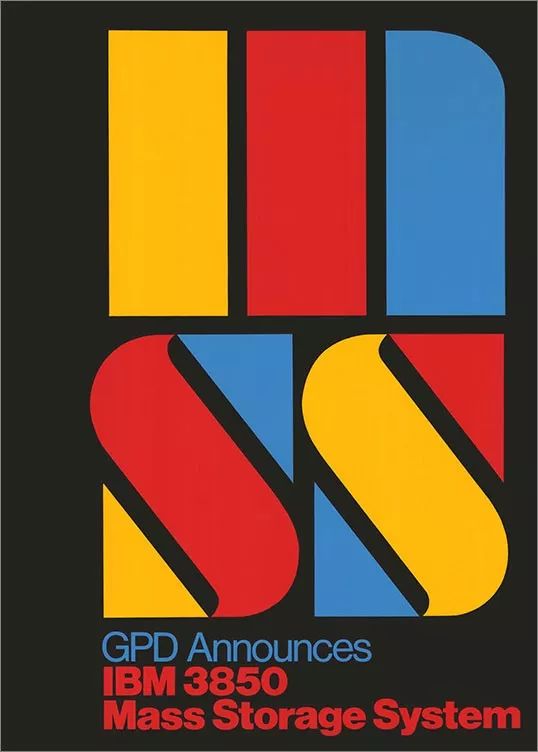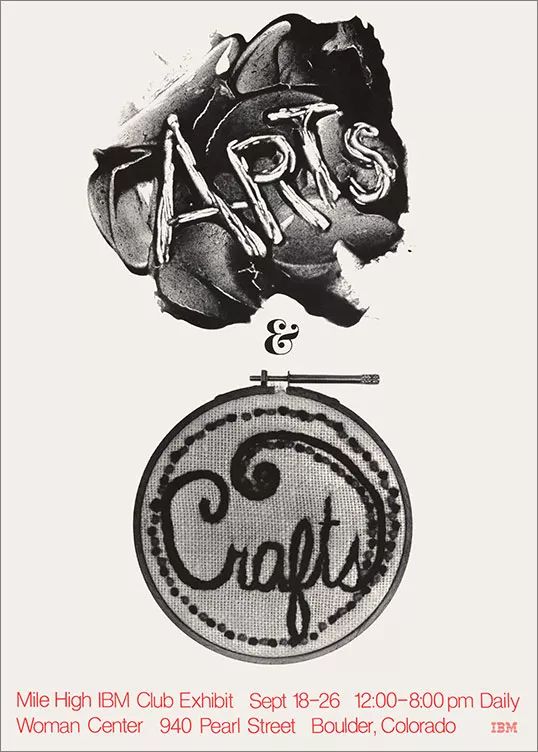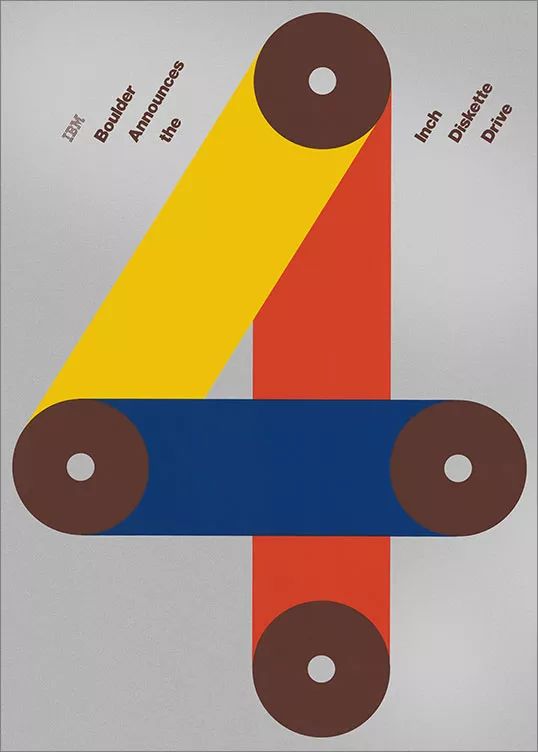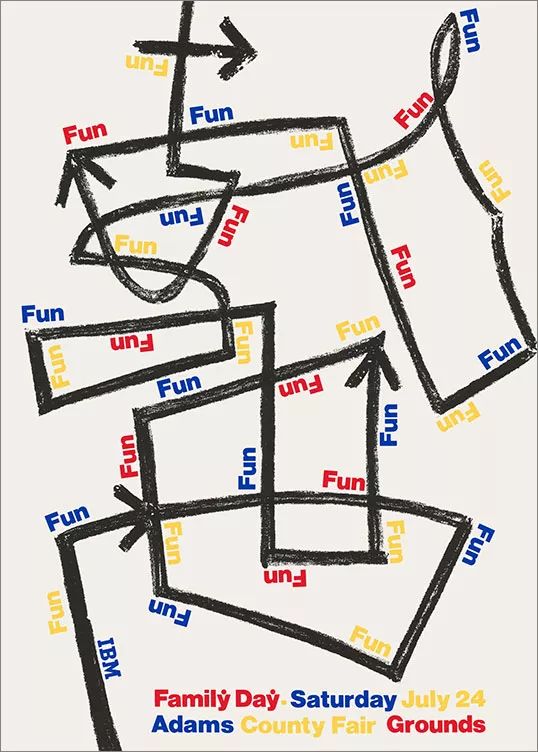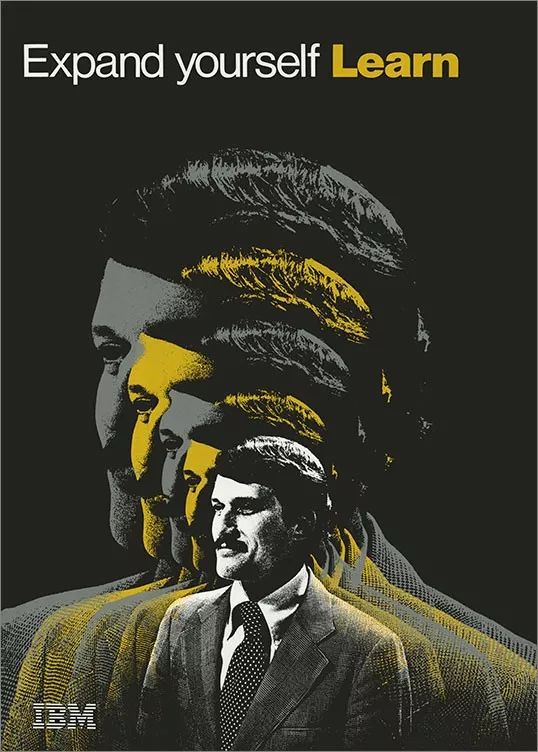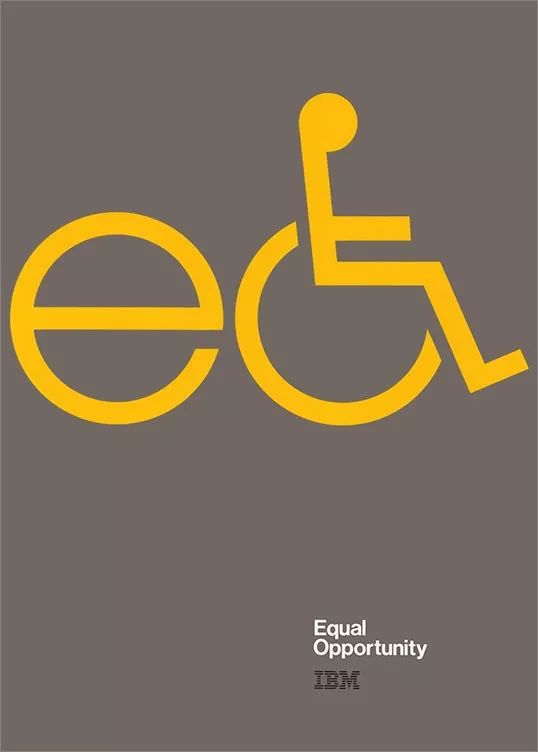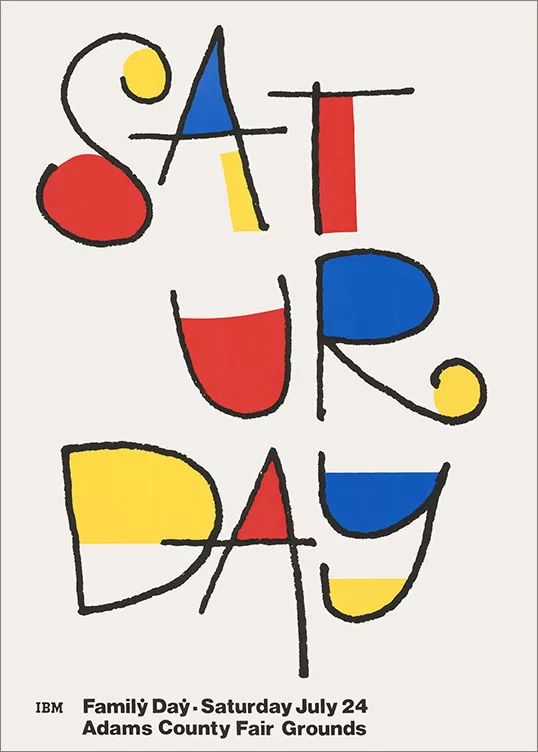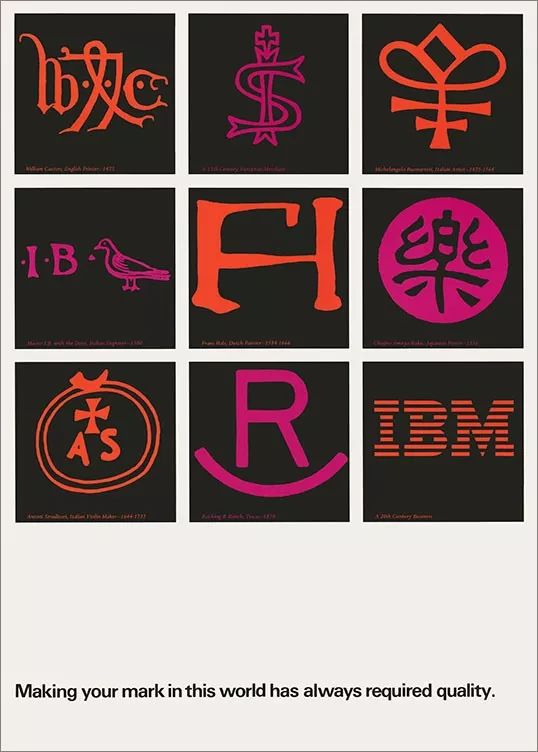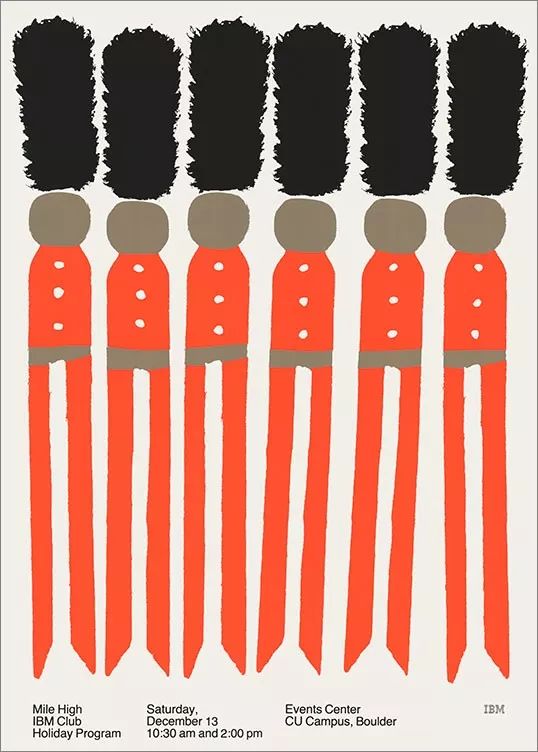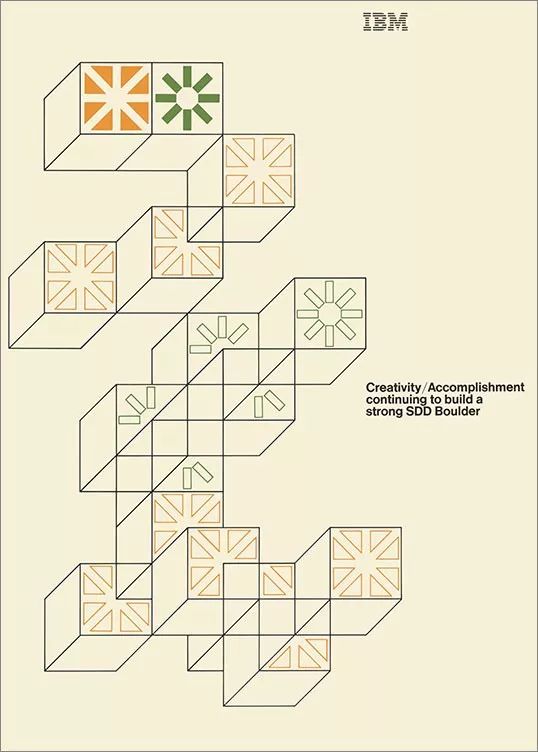
看了这些20世纪60年代的海报,震撼!
在二战之后的几十年,IBM迎来前所未有的增长时代,在这期间,IBM总裁Thomas J. Watson通过聘请世界知名设计顾问,包括兰德·保罗,艾略特·诺伊斯,查尔斯和雷伊姆斯,作为提升IBM具有前瞻思维,技术先进的组织的形象。
其中兰德·保罗设计的IBM徽标,对IBM内部员工设计师产生了非凡的影响。
上图IBM的招贴设计,是兰德的传世之作,作为一名“功能主义者”和“实用主义者”,他在内容和形式之间划出了严格的界限,一个眼睛、一只蜜蜂和一个M代替了IBM传统logo:“I”设计成眼睛,是对人的关爱;“B”设计成蜜蜂图形,代表的是辛勤劳动;“M”信息与科技,是对技术的不断创新。把这些符号元素进行意义上的分解,然后再将各种符号信息重新组合。体现了IBM一直在锐意创新、辛勤劳动并积极进取的精神。风格独特又构成得和谐自然,显现出设计的创造价值,体现了科学与艺术的结合,合乎观众的接受心理。
而这次由纽约字体艺术指导俱乐部(TDC)精选的Visual Memoranda: A Selection of Posters from the IBM Poster Program 1969-1979(IBM1969-1979海报选集)它展现了IBM在20世纪60年代后期的一系列海报设计。
下面来看一下部分展出的海报:
EXPAND YOURSELF: LEARN, 1975
设计:Ken White
摄影:Rodger Ewy
4-INCH DISKETTE DRIVE, 1969-79
设计:Tom Bluhm
FAMILY DAY, 1969–79
设计:Tom Bluhm
IBM MILE HIGH CLUB EXHIBIT, 1969–79
设计:Tom Bluhm
MASS STORAGE SYSTEM, 1974
设计:John Anderson
EQUAL OPPORTUNITY, 1969–79
设计:Tom Bluhm
U.S. SAVINGS BONDS | PRESERVE THE FUTURE, 1969–79
设计:Tom Bluhm
摄影:Rodger Ewy
SERVICEABILITY: IT SAVES, 1969–79
设计:Tom Bluhm
MILE HIGH IBM CLUB HOLIDAY PROGRAM, 1969-79
设计:Tom Bluhm
MILE HIGH IBM CLUB ARTS AND CRAFTS EXHIBIT, 1969–79
设计:Tom Bluhm
MAKING YOUR MARK IN THIS WORLD HAS ALWAYS REQUIRED QUALITY, 1976
设计:Ken White
CREATIVITY / ACCOMPLISHMENT (DISCOVER), 1970
设计:Ken White and Gerald Cross
NATIONAL INVENTORS DAY, 1969–79
设计:Tom Bluhm
A DIPLOMA FROM THE SCHOOL OF HARD KNOCKS, 1972
设计:Ken White
GIVE BLOOD, 1974
设计:Ken White
DO YOU HAVE A NEED TO NO?, 1973
设计:Ken White
FAMILY DAY, 1969-79
设计:John Anderson
CREATIVITY / ACCOMPLISHMENT: CONTINUING TO BUILD A STRONG SSD BOULDER, 1969–79
设计:Tom Bluhm
LOCK YOUR DESK AT
QUALITY, EXCELLENT, ELEMENTARY, 1969–79
设计:Ken White
摄影:Rodger Ewy
这个展览于6月6日至8月1日在纽约展出,同时,策展人Robert Finkel和Shea Tillman为这次展览创建了网站,为未能亲临现场欣赏海报的观众提供了便捷的方式。